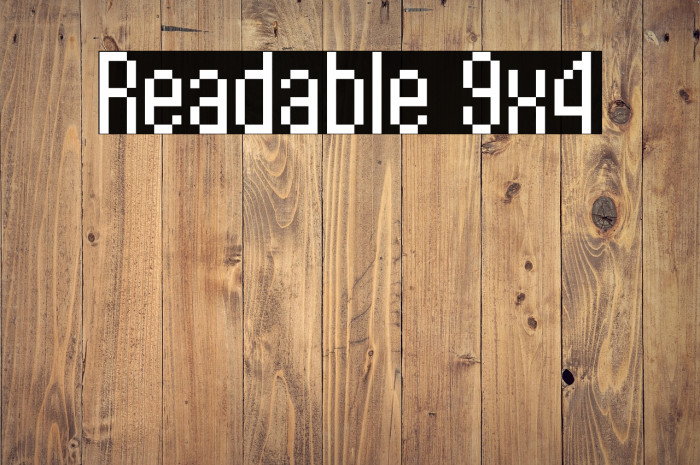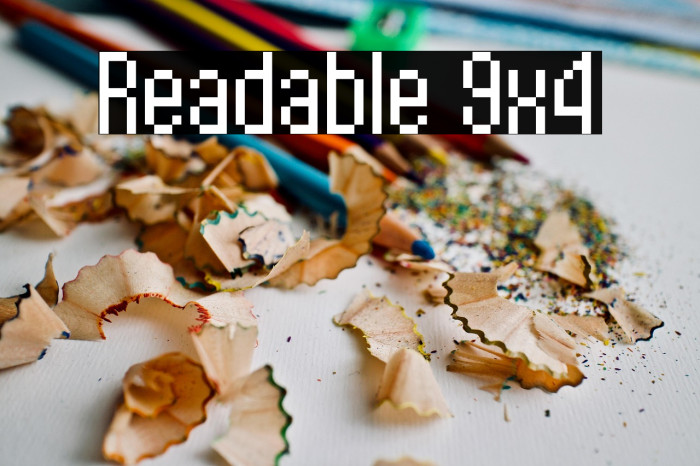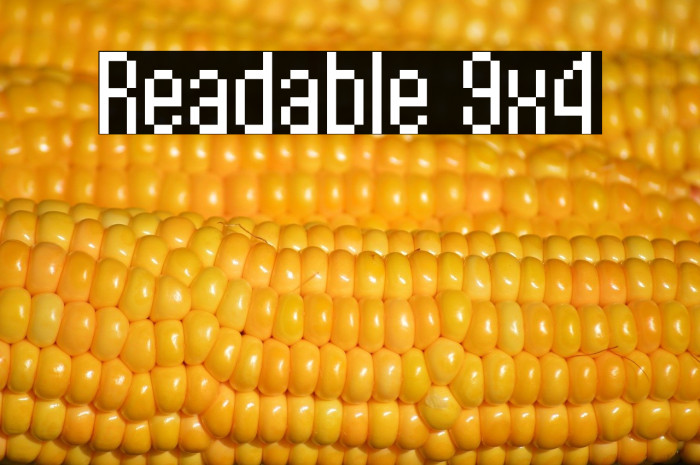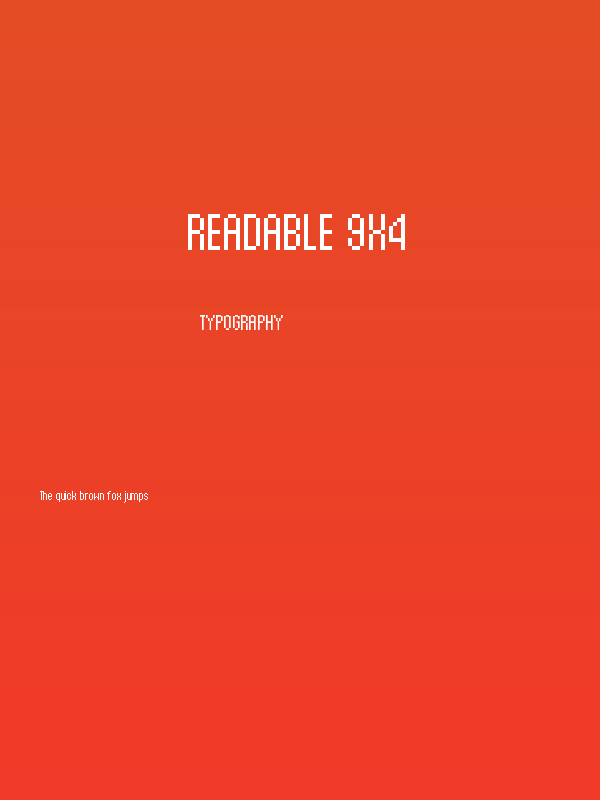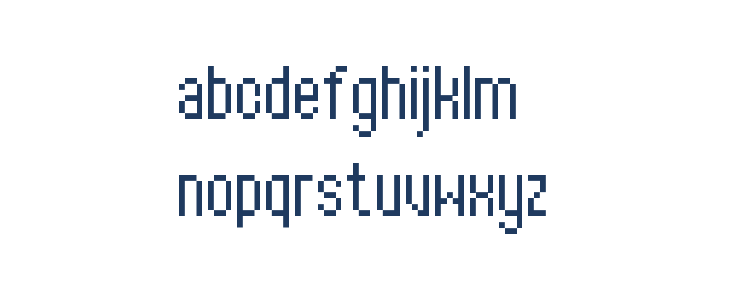
Readable 9x4 Font
| Gesamtstil | Retro |
| Anwendungsfall | Digital displays, Coding, Retro-themed projects |
| Vorgeschlagene Projekte | Ideal for retro video game design, digital displays, coding environments, and nostalgic-themed projects. |